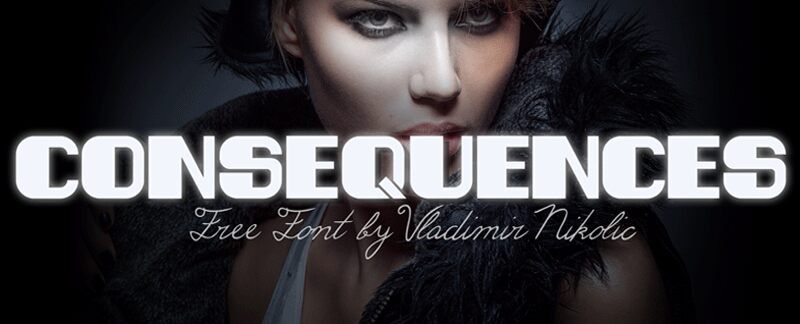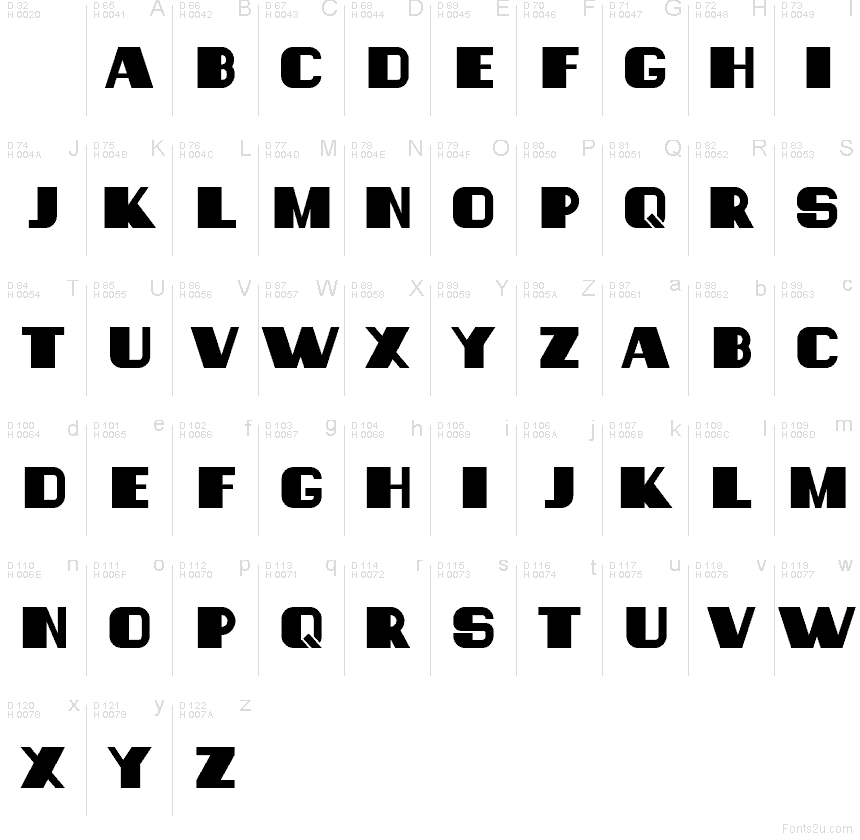
Consequences Flat autorstwa Vladimira Nikolica to darmowy, retro font typu display o wyrazistym, blokowym charakterze, przywodzący na myśl plakaty z lat 70. Litery są zamknięte w ciężkie, geometryczne formy z zaokrąglonymi rogami i szerokimi wycięciami, dzięki czemu font wygląda solidnie i masywnie, zachowując przy tym lekkość.
Naturalnie sprawdzi się na okładkach albumów, plakatach festiwalowych, tytułach, opakowaniach oraz odważnych nagłówkach, gdzie potrzebny jest gęsty, vintage'owy klimat. Jako darmowy font świetnie nadaje się również do monogramów, krótkich logotypów i inicjałów, ponieważ jego szerokie, wycięte kształty przyciągają uwagę bez potrzeby stosowania dodatkowych ozdobników.
Klasyczny i czysty font bezszeryfowy. Świetny do brandingu, logotypów, tytułów, oznakowań, plakatów, ulotek, projektów na koszulki, nagłówków i wielu innych zastosowań!